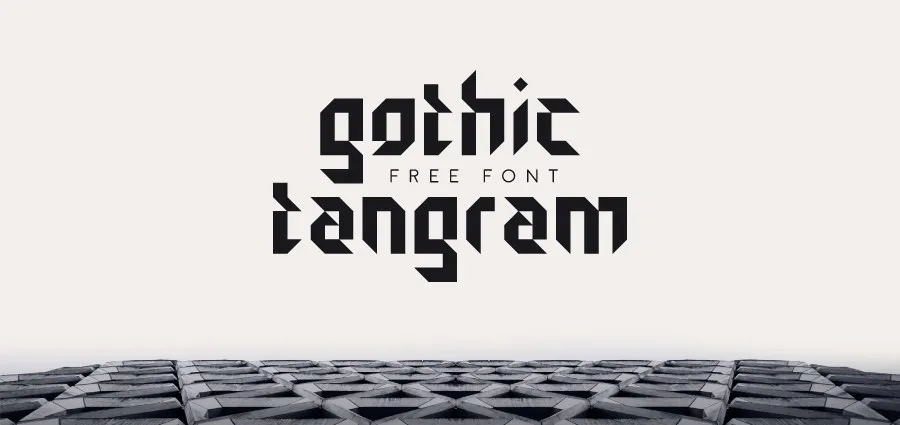
Gothic Tangram Font – Download Grátis
Introduzimos uma nova fonte chamada Gothic Tangram, criada por Pedro Pazetto. Esta fonte é uma inovação na categoria de fonts gothiscas, oferecendo um estilo moderno e distinto que se adapta perfeitamente a qualquer tipo de projeto gráfico. Gothic Tangram não apenas traz beleza à sua próxima criação visual, mas também uma nova dimensão ao seu design. Com linhas retas e robustez clássica do gothic style, esta fonte é ideal para uso em cabeçalhos ou em qualquer tipo de texto que deseja destacar. Seu designer, Pedro Pazetto, tem um talento excepcional para criar fontes elegantes e únicas que se tornam verdadeiros destaque nos mais diversos projetos. Agora você pode adicionar ainda mais personalidade a seu trabalho com esta fonte gothic clássica e moderna. Sua versão ‘Gothic Tangram Font’ é perfeita para designers gráficos, editoriais de moda ou qualquer um que busque uma fonte elegante e única para seus projetos. Descubra por si mesmo o poder desta nova fonte gothic tangram.